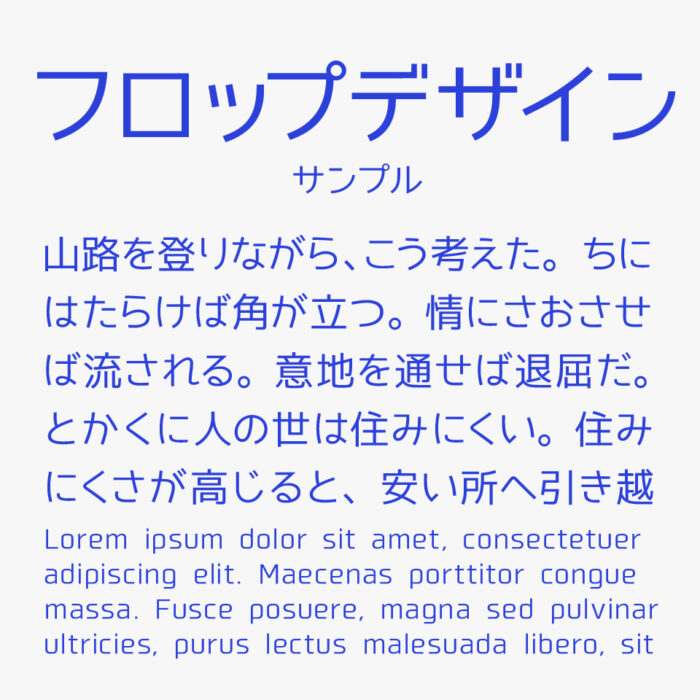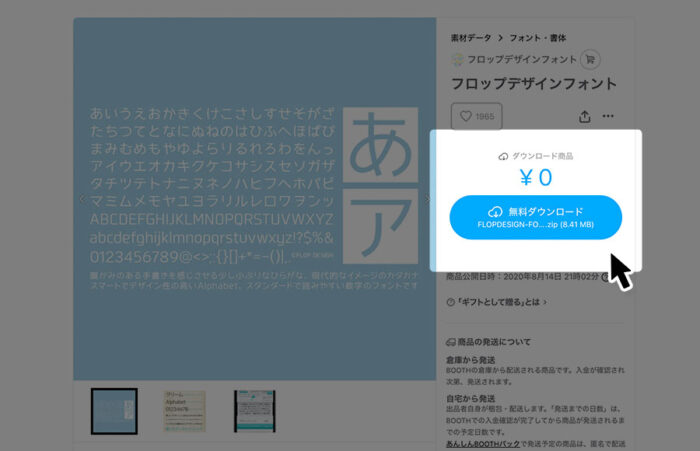
フロップデザインフォントは、シンプルなゴシック体をベースにしながら、手書き風のやわらかい曲線を取り入れた温かみのあるゴシック体フォントです。
水平・垂直の直線を基調としたデザインがスマートでモダンな印象を与える一方で、仮名文字にはゆるやかな曲線が施されており、やさしく柔らかな雰囲気を感じさせてくれるフォントです。
また、文字のバランスが整っているため、長文でもストレスなく読み進められる高い可読性を兼ね備えています。